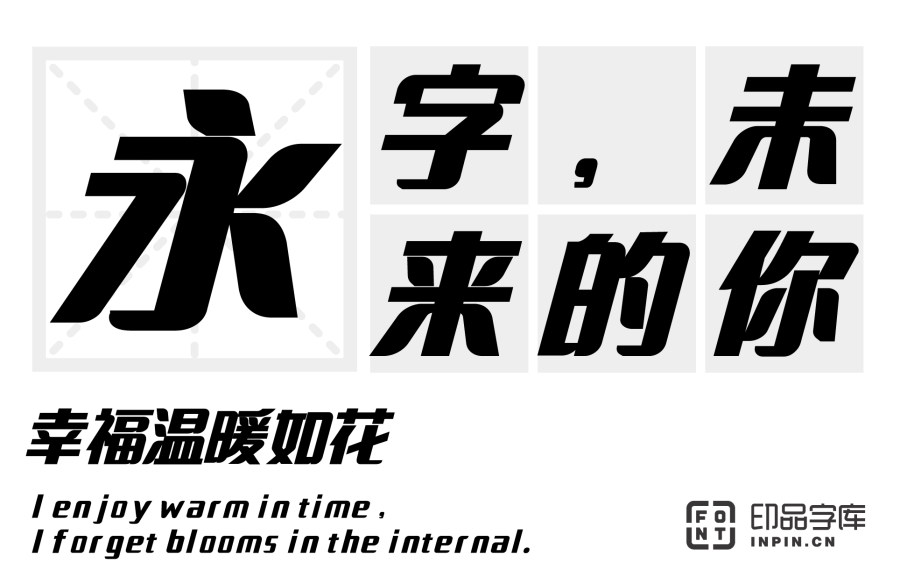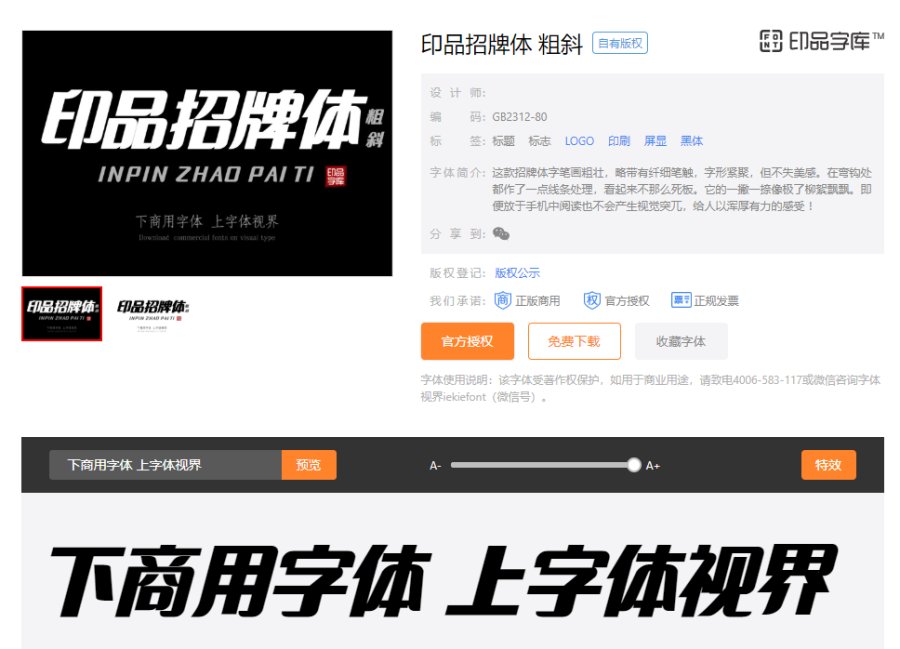
印品招牌体 粗斜,印品招牌体系列字体中的一一款,创作于2019年,是一款很适合招牌的字体。粗壮有力的黑体是被广泛使用的基本字体,不管是手机端还是电脑端基本上都是主流的屏显字体。这款印品招牌体 粗斜,相比于传统的黑体,更加圆润,让人感觉更加舒适。黑体字笔划整齐划一,它浑厚有力,朴素大方并且引人注目。设计师在设计、做字过程中,做了一些细节调整优化。它的弯钩都作了一点线条处理,看起来不那么死板。它的一撇一捺像极了柳絮飘飘。印品招牌体 粗斜主要笔画粗壮,带有纤细笔触,字形紧聚,但不失美感。